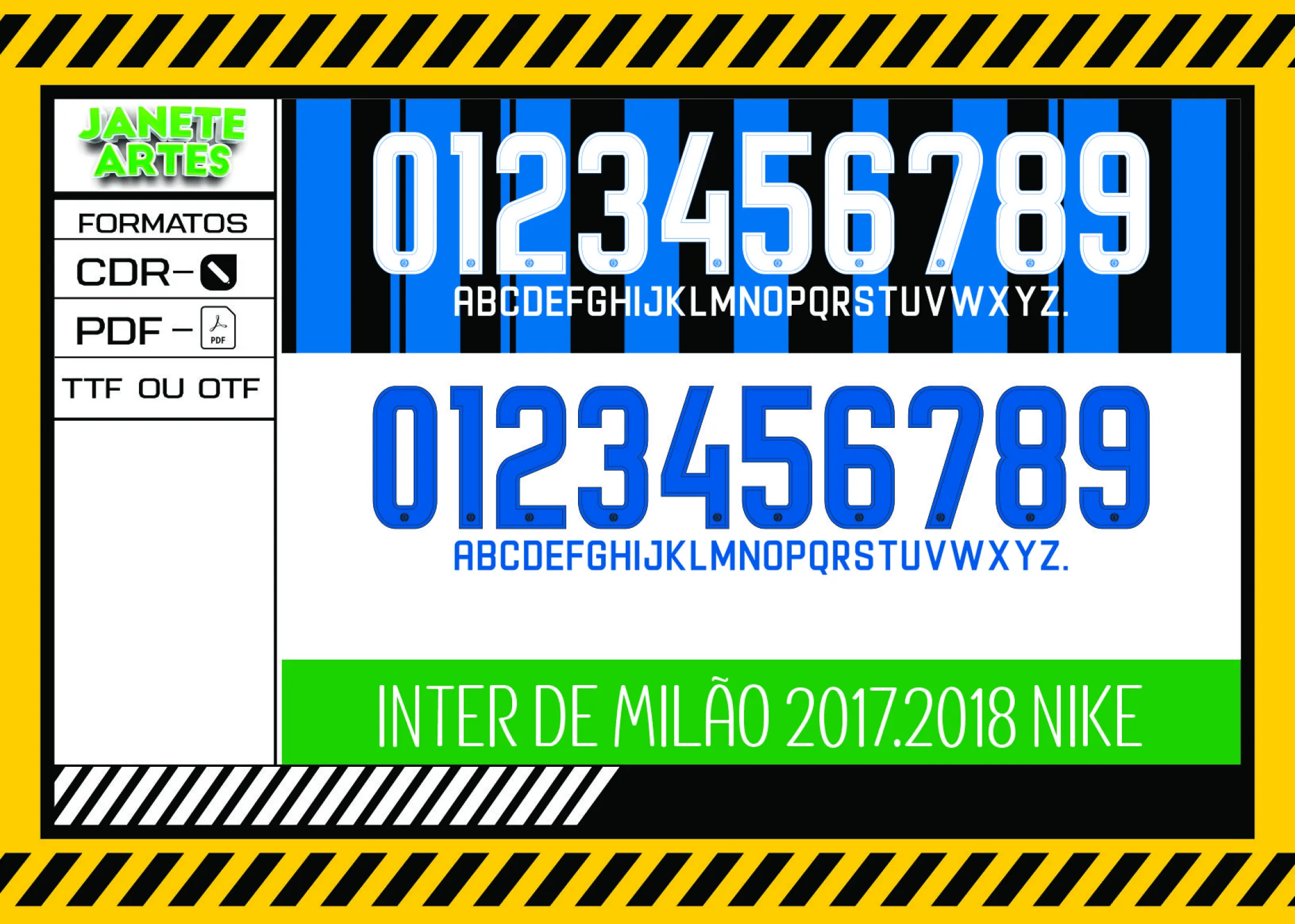
Camiseta unissex preta com logo no peito e estampa grande nas costas, apresentando a fonte do time Inter de Milão 2017 - 2018 em design moderno e marcante.
Fonte de Time Tipografia Inter de Milão 2017 - 2018
Conheça a Fonte de Time Tipografia Inter de Milão 2017 - 2018, perfeita para personalizar camisetas e criar designs únicos com o estilo do time italiano. Ideal para torcedores e eventos esportivos.
Uma paixão que vira estilo
Imagina vestir a energia e a história do Inter de Milão com uma camiseta personalizada só sua? Foi assim que Ana descobriu a Fonte de Time Tipografia Inter de Milão 2017 - 2018. Fã do time desde pequena, ela queria um jeito especial de mostrar seu amor nas partidas do campeonato. Ao baixar o arquivo, Ana criou uma camiseta exclusiva, com a fonte original do clube, que virou sucesso entre os amigos. Hoje, ela sempre recebe elogios pela ousadia e estilo único que leva para a torcida. Essa história mostra como um detalhe faz toda a diferença!
• Combine a fonte com cores fortes como preto e vermelho para um visual vibrante;
• Use em camisetas básicas para destacar o design do time;
• Experimente criar estampas grandes nas costas e logos menores no peito para um efeito profissional.
Agora que você conhece todos os detalhes da Fonte de Time Tipografia Inter de Milão 2017 - 2018, aproveite para criar sua camiseta exclusiva e mostrar sua paixão pelo time com muito estilo! Essa fonte é o toque que faltava para suas peças ficarem incríveis e cheias de personalidade.